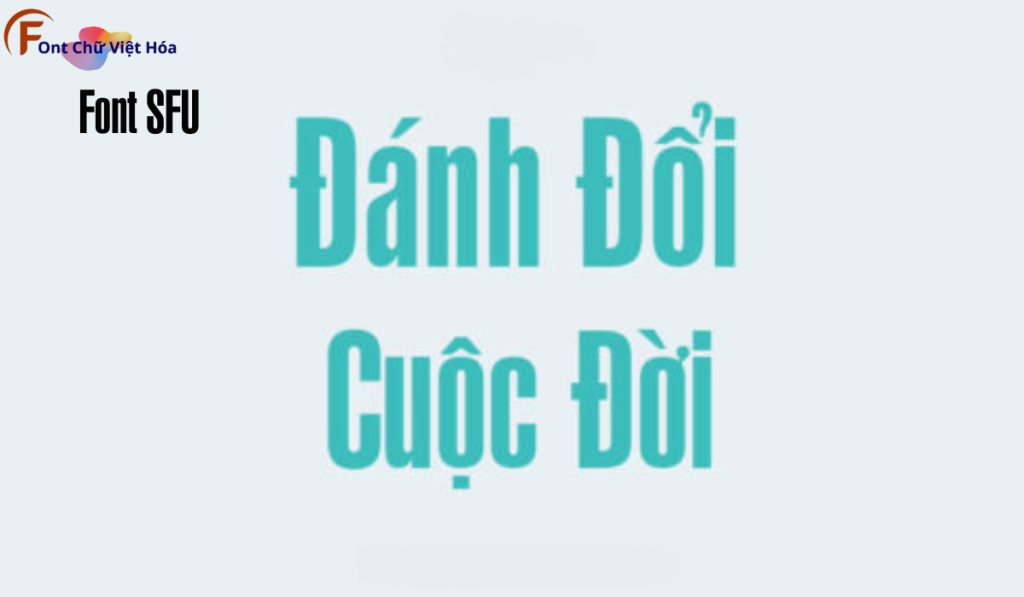
SFU Swiss Font Việt Hóa
Tác giả: SFU
Bộ Font: SFU
Phân loại: Hiện đại, Thanh lịch
Font SFU Swiss Việt Hóa là một font chữ độc đáo, thuộc bộ SFU, mang phong cách sans-serif hiện đại với các đường nét thanh thoát và tinh tế. Thiết kế của SFU Swiss tập trung vào sự rõ ràng và dễ đọc, đặc biệt phù hợp cho các thiết kế đòi hỏi tính thẩm mỹ cao như poster, logo, và tiêu đề. Với tỷ lệ chữ cân đối và các đường nét sắc sảo, font này tạo ra ấn tượng thị giác mạnh mẽ và giúp tối ưu hóa không gian trong thiết kế. Font này cũng đã được Việt hóa, mang đến sự linh hoạt và tiện dụng cho các dự án thiết kế bằng tiếng Việt.